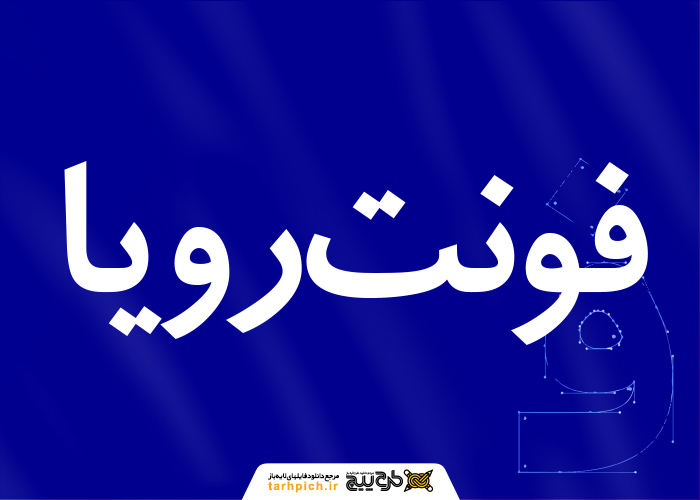
فونت رویا
لینک دانلود فونت فارسی رویا با فرمت‌های گوناگون در اختیار شما نیز قرار می‌گیرد. شما با هر فرمتی که بخواهید می‌توانید دانلود  فونت رویا را انجام دهید و از آن در  نرم‌افزارهای مانند فتوشاپ و اینشات استفاده کنید. برای خرید طرحهای گرافیکی به صفحه اصلی سایت مراجعه کنید.فونت فارسی رویا حالتی رسمی دارد و مناسب برای طراحی  های رسمی و آموزشی است .طراح فونت رویا آقای ابوالفضل سیل سپور است .اگر به دنبال طرح های گرافیکی زیبا برای دانلود فونت جدید فارسی برای خود هستید کافیست روی لینک های مربوطه کلیک نمایید.